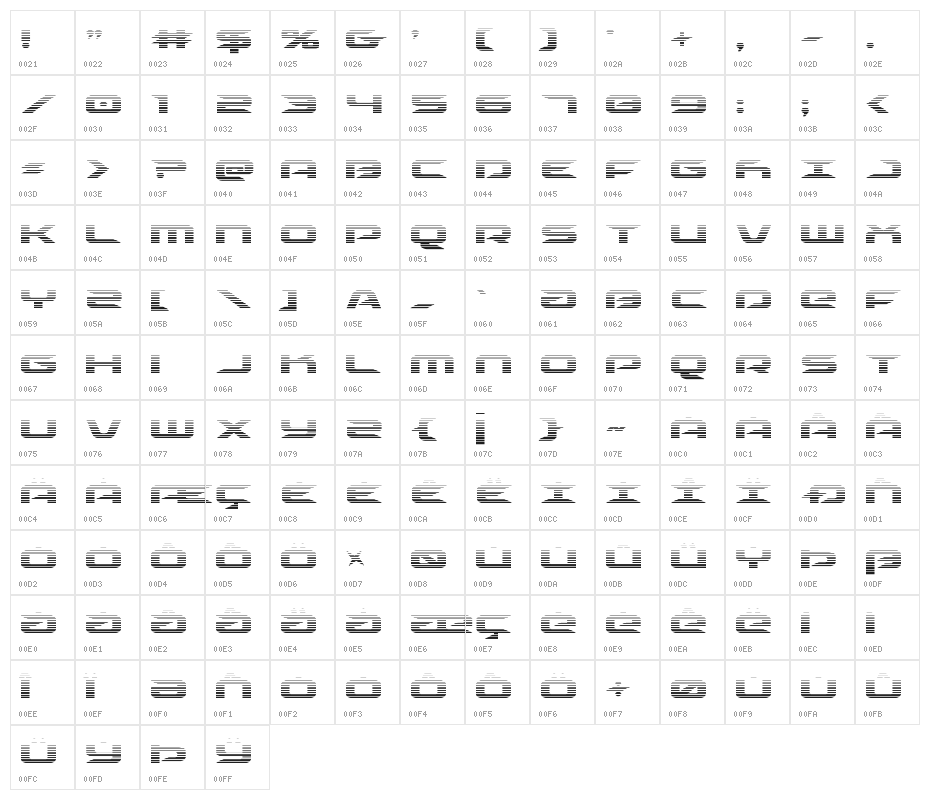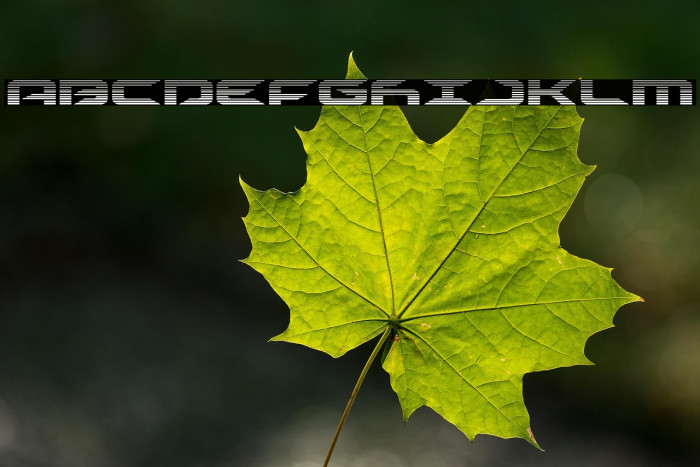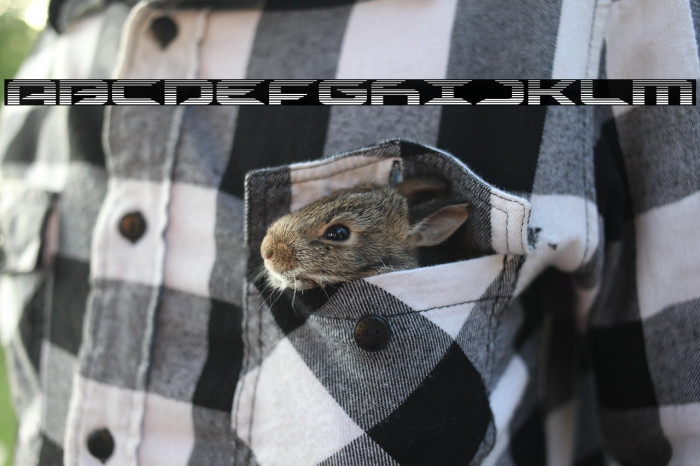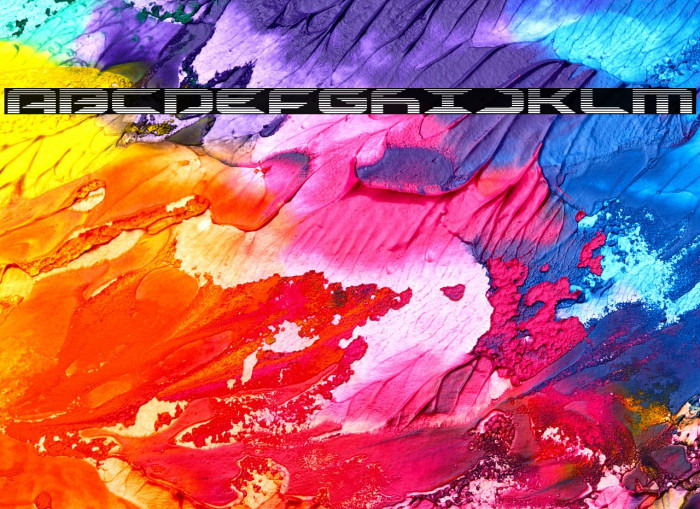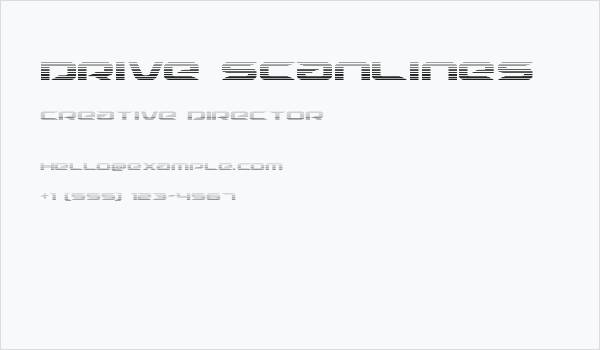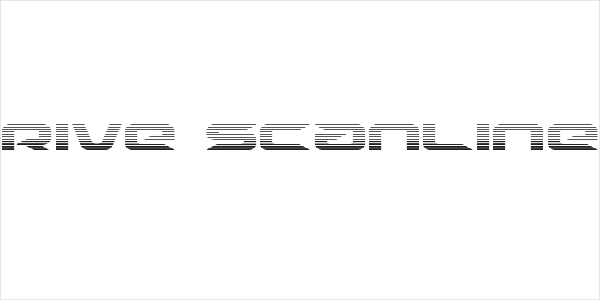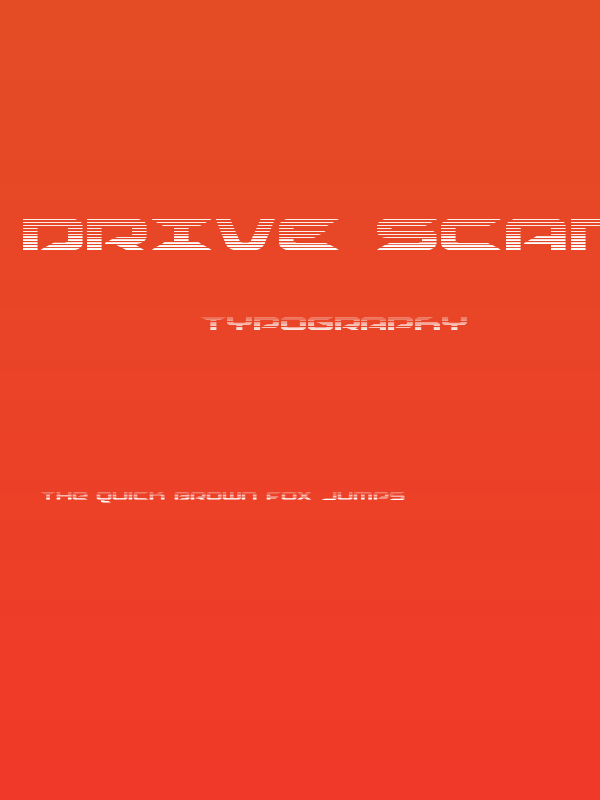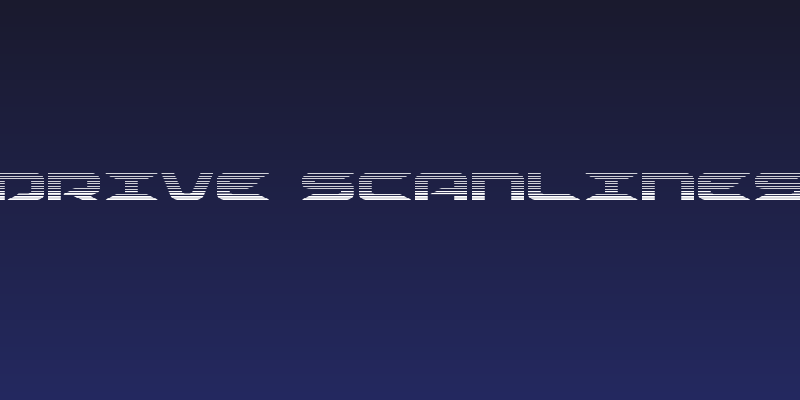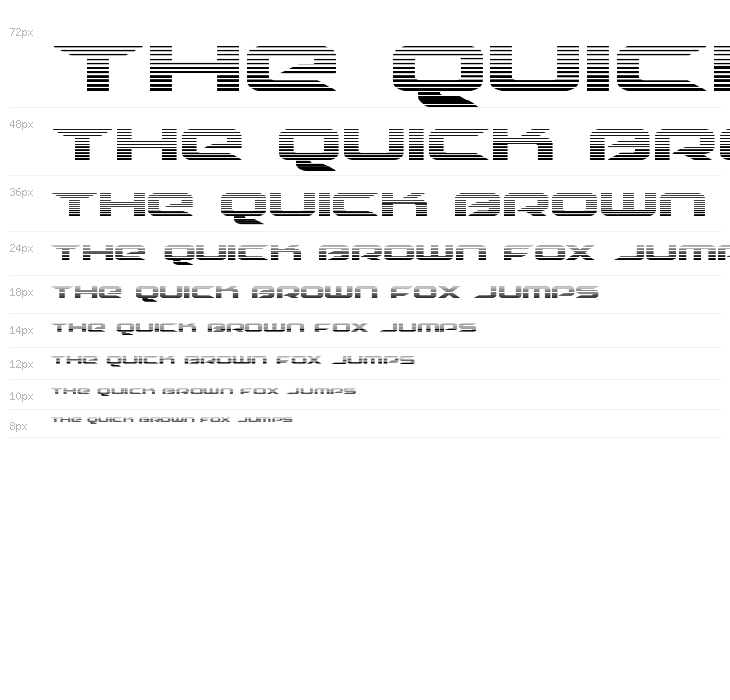
Drive Scanlines Font
| Proyectos propuestos | Ideal for tech-themed designs, sci-fi movie posters, video game interfaces, and digital art projects. |
Drive Scanlines